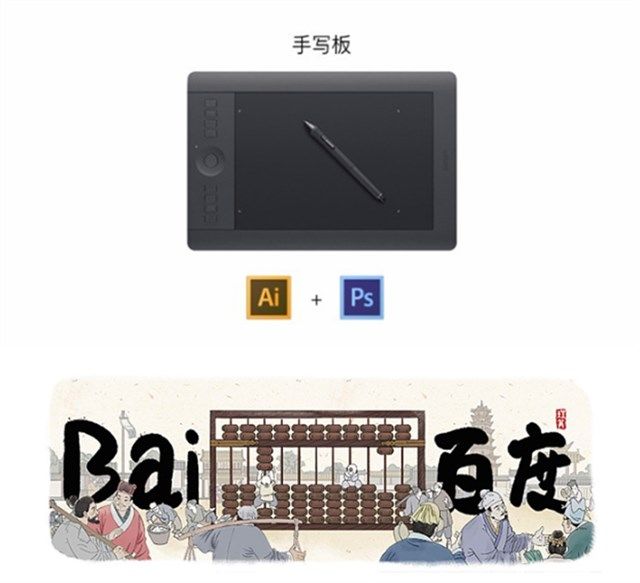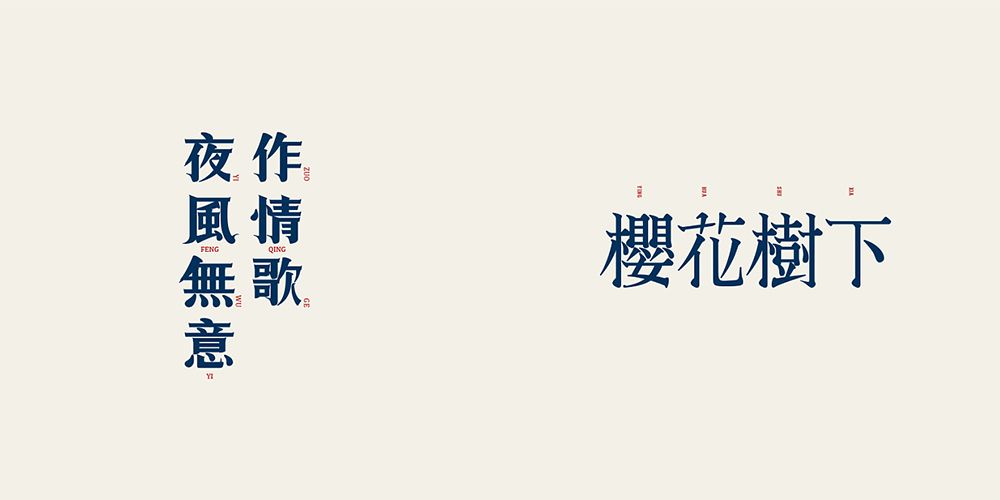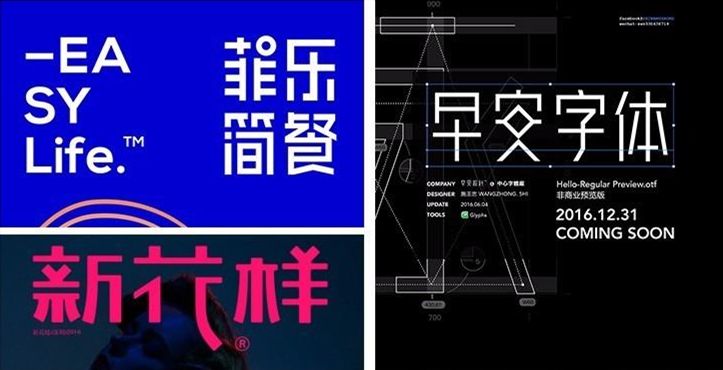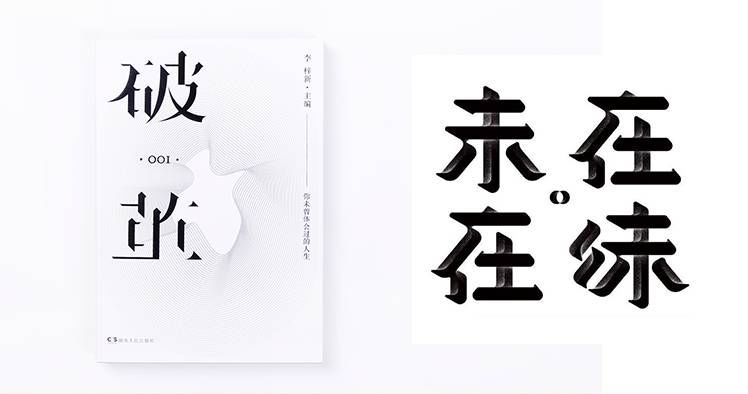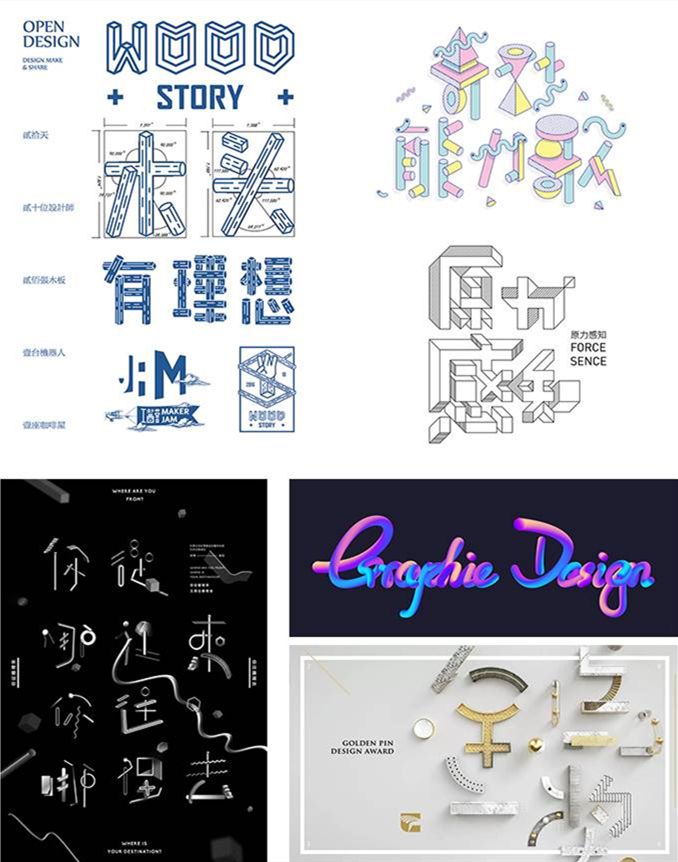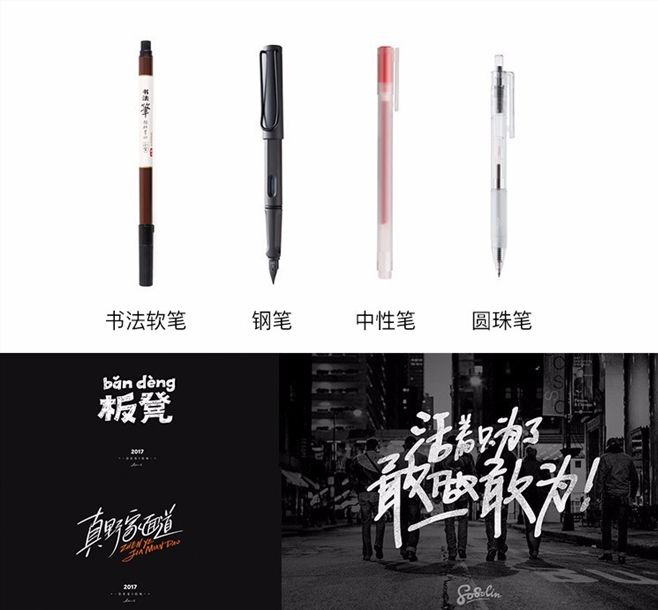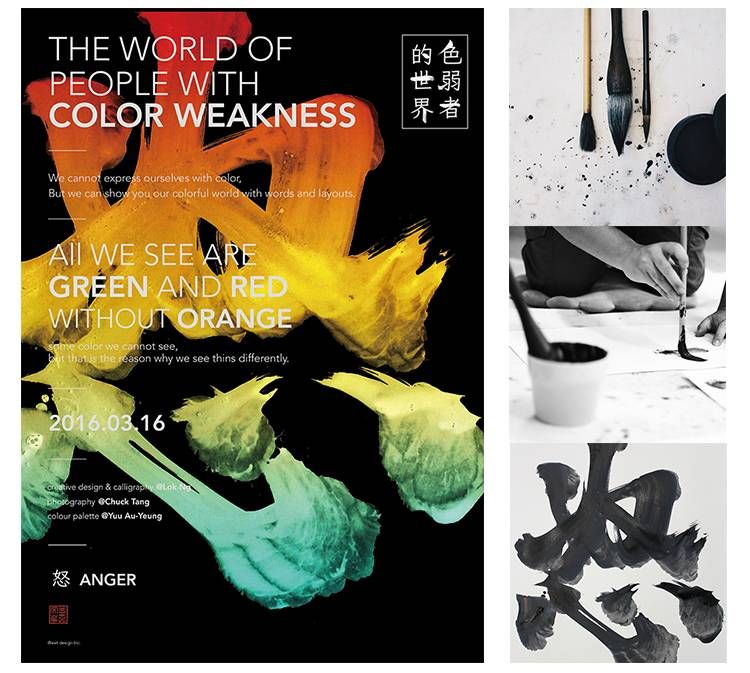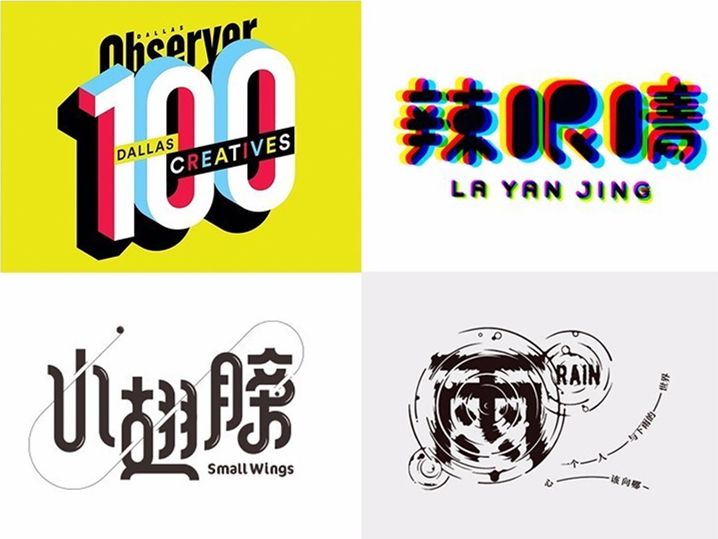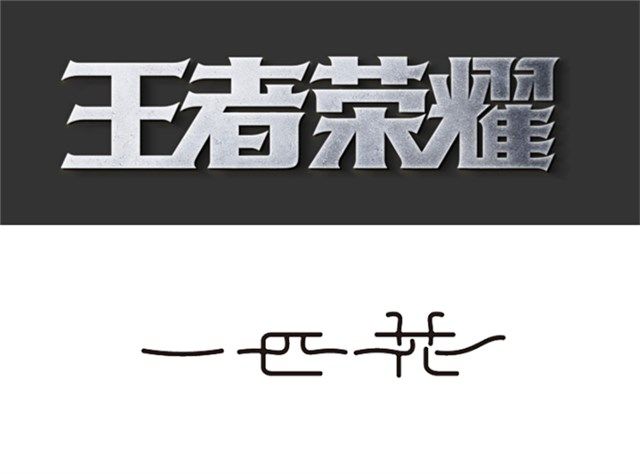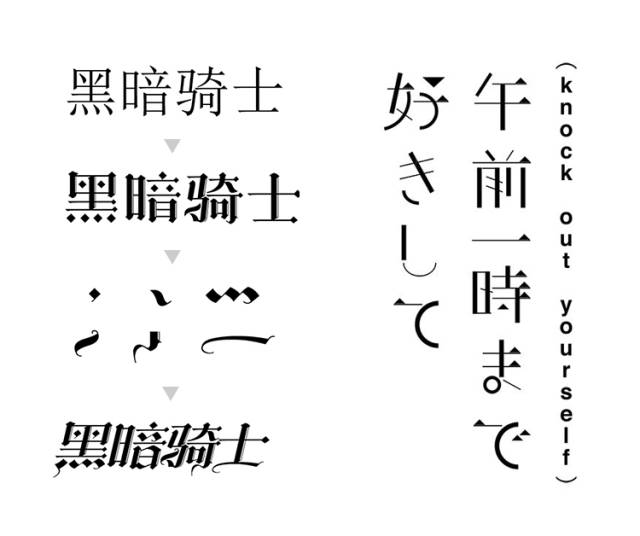
字体设计,就靠这篇干货了!
前言:在视觉设计工作中,几乎所有都会使用到字体。字体设计不同于字体库字体,它是经过艺术性加工和升华的字体,对比字体库千篇一律,个性不强的字体,字体设计展现的魅力更加独特与诱人。所以今天大大君想要分享一篇字体干货,让大家突破字库字体的桎梏,激发大家做字体的灵感。
字体表现类型
那么做为字体小白,如何从基础开始有系统性的学习字体设计呢?下面将以中文字体做主要分析,根据喜闻乐见的字体设计案例,我们大致将字体表现类型分为五种:黑体字、宋体字、书法体字、三维体字、动态体字。
黑体字
黑体字也叫等线体,又称“方体”,属于无衬线字。字架吸收了宋体字结构的优点,去掉了衬线装饰,整体简洁大方,有时尚感和现代感。
黑体字可以说是百搭字体,可塑性很强,可以表现商业的严谨气质,也可以表现青春激情和动感,纤细的黑体还能体现女性气质。
宋体字
宋体字是为印刷而生的,其笔画有粗细变化,一般是横细竖粗,笔画末端有类似三角形的节点衬线装饰。宋体属于衬线体。
宋体的装饰性远大于黑体,宋体字形在文化、艺术、生活、女性、美食、养生、时尚等领域所传达出的气质要比黑体字形准确。
书法体字
中国书法字讲究行气,指书法作品中字与字、行与行之间的呼应关系。一般要求笔断意连,连缀成行,积行成篇,在文字的上下、左右、首尾的书写中,既有变化,又能和谐。书法字自身孕育的大气恢弘之势,可以承载出无限的设计能量。
毛笔字书写实现案例
其他书写做字工具
三维体字
三维体指有3D效果,立体感,空间性强的字体。常见是辅助60°、45°网格绘制,各个透视组建,按照基本字形组合搭建而成。
横平竖直的结构比较容易实现,撇、点、捺需要设计师丰富的创作能力去实现。或者将字型笔画拆解,用立方体、圆柱体或其他几何体取代常规笔画,任意组合,可以创造出无尽的字体可能。当然也可以直接用如C4D等三维软件,根据字型建模渲染。
动态体字
静态字体有自身表现的局限性,如果增加动效可以增强感官感受,也能将字义表现的更到位,使人印象深刻。
字体基础改造方法
汉字是方块字,为了达到视觉上的感官平衡,在字形空间上是有一些基础规律可循的,简单粗暴的总结为三种结构表现方式:上紧下松、横细竖粗、左窄右宽。但最重要的是字体重心。
汉字的重心和我们理解的几何重心是不同的。字体重心是一个字最吸引视线的重心,也称为视觉重心。简单来说,视觉中心在几何中心偏左上方一点的位置。比如在米字格中,对角线的交叉点就是几何中心,而交叉点左上方一点的位置才是视觉中心。
设计中为了达到字体的整体平衡,一个字中较重的部分要靠近字体重心,较轻的部分则要离重心稍远些,这样能使字达到视觉美感平衡。一般来说,一个字的主体部件和次要部件在布局上处理成黄金比例,那么这个字在视觉上就平衡了,看起来也会更加舒适美观。
黑体字与宋体字是所有汉字字形的基础,它们有严谨的字体结构,所以练习字体设计,均从黑体字与宋体字开始。
有了字形,我们还需要根据字义进行变形。由字义到字形的设计过程是一个由内而外,由虚至实的思维过程,从核心字义出发,从字体内容出发,才能有一个准确的设计起点,最终设计出内外兼修的字体。
以下有8种简单的方法,可以让基础字型成为内外兼修的好字型。
在原有字体基础上,删减某一处或多出笔画之后,再用其他形式进行代替,可以用其他字体笔画做衔接,也可以用图形图像的添加,方式很灵活。
或者采用具有象征性的视觉图形符号,唤起人们对某一个抽象意义、观念或情绪的记忆。能正确传达与理解象征的意义,表达出字体的含义与气质。
根据字体主题进行针对性的设计修饰,常常是在横竖撇捺的笔画端点处进行锚点添加,或断点处理。
笔画有快手的组合形式,比如笔画太多太复杂,为了简单粗暴的表述,我们先以横线来做示范。
男性字除了可以把笔画变粗,还可以这样:
女性字除了可以把笔画变细,还可以这样:
男性字与女性字笔画对比
(上男下女)
在保证字体识别度的前提下,对笔画进行减法留白处理,因为人脑可以根据自己的视觉经验将隐藏或省略的部分在脑中自动补齐。这种方法处理的字型比较有东方绘画的韵味,文艺气质浓厚。
运用圆角、描边、倾斜等系列工具对原字体笔画进行显著的外形变化。圆角工具可以把笔画转折处变直为曲,描边工具可以使字体加粗或减细,倾斜工具可以加强字体的力度与动感。
拆解出外文或标点符号独特的笔画装饰,按照汉字的字形结构来组合。一般使用比较多的是哥特字体、藏文、中世纪的手写卷花体等。
在设计好的基础字型周围添加放射线、波点等几何形,或者花型,来烘托气氛,对字体含义的表达起到辅助作用。
通过丰富的色彩、光线阴影、质感叠加、具象或抽象的图案纹路让字体变得生动活泼。
透视、虚实(景深)、羽化模糊、视幻、点化群集、重叠遮挡、投影、正负反向等手法来塑造字体空间的丰富性。
总结
可以称之为“高级感”的字体,一般带有如下特征:
不加修饰
纯粹
耐看
结构端正
经得起推敲
字型带有美感与张力
设计师需要进行大量的练习,才能真正领悟字体设计的精髓,根据需求游刃有余地将字体设计融入到平时的设计工作中。